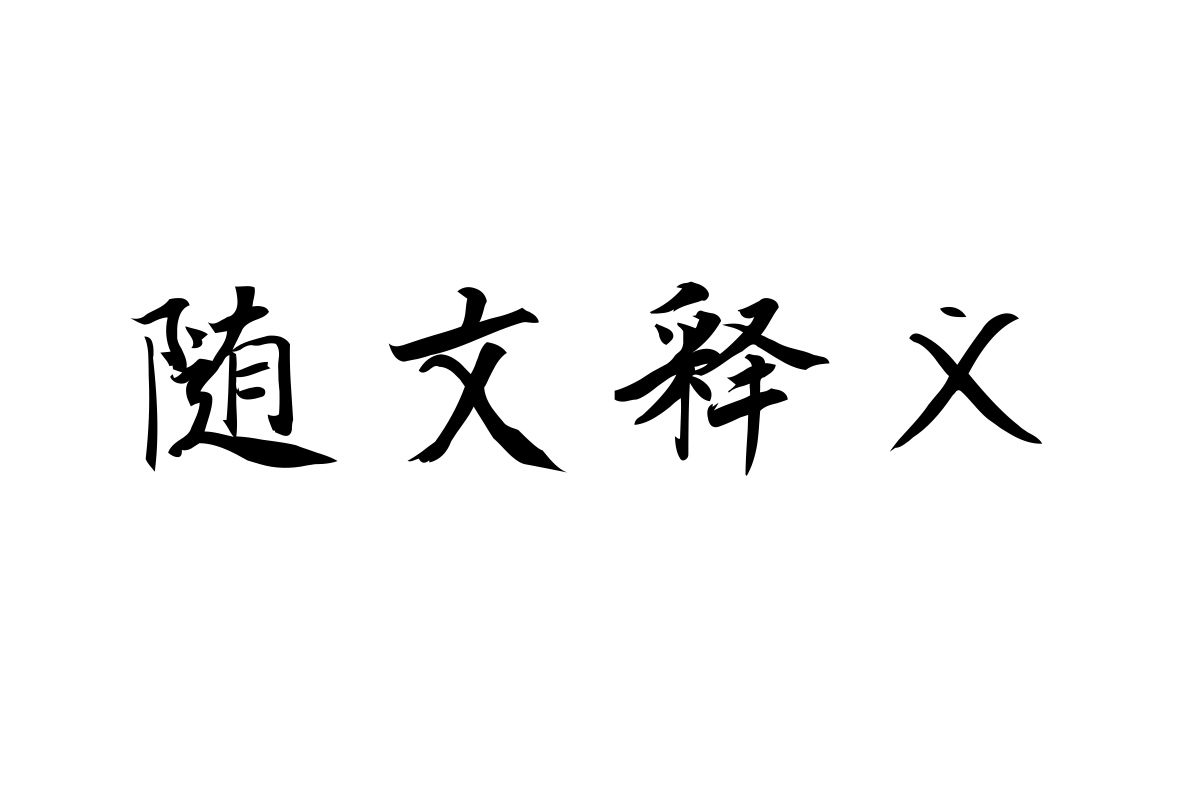
蝉羽金帛手书是一种手写体,其特点是笔画流畅、结构紧凑。这种字体的特点是笔画粗细变化明显,线条流畅,给人一种优雅的感觉。同时,它的结构紧凑,每个字的笔画都紧密相连,使得整个字体看起来非常协调。
蝉羽金帛手书的笔画粗细变化主要体现在笔画的开始和结束处。一般来说,笔画的开始处较细,而结尾处则较粗。这种粗细变化使得整个字体看起来更加生动有趣。
此外,蝉羽金帛手书的字形也有一定的规律性。例如,某些字的笔画顺序可能会有所不同,但整体上仍然保持一定的一致性。这使得读者在阅读时能够更好地理解和记忆这些字。
总的来说,蝉羽金帛手书是一种具有独特美感和艺术性的手写体,它以其流畅的笔画和紧凑的结构吸引了许多书法爱好者的喜爱。